2025年4月22日至4月26日,第66届国际字体大会(AtypI)在丹麦哥本哈根举行,这是ATypI第三次重返北欧设计之都哥本哈根。此次大会以“AI与参数化设计在字体设计中的应用”为主题,汇聚全球顶尖设计师与技术专家,深入探讨进入数字化时代后,人工智能对于重构文字的表达方式与阅读体验带来的影响。
历史和现代优雅交叠的哥本哈根,既充满文化底蕴又不失创新意蕴。1973年ATypI 首次造访时,排版作家 Nicolete Gray 曾有一场关于“非自愿的公共阅读方式”的演讲,首次系统性地揭示了公共空间中文字的无意识渗透现象。
如今,Nicolete Gray在演讲中提到的公共阅读的物理形式已经逐渐变迁,进入互联网时代,受到数字化的影响,我们大多接收到的信息以及字体都是基于屏幕产生,且越来越多的字体由人工智能生成。基于此,ATypI提出新的疑问,数字化的阅读意味着什么?会在字体设计上产生怎样的影响?
作为中文字体领域的开拓者与引领者,方正字库此次携两大核心演讲亮相ATypI,不仅展现了AI时代汉字技术的革新力量,更以东方智慧为全球字体设计注入新灵感。现场吸引了众多与会者的讨论与思考,为中文字体在国际化舞台的发展提供了重要的力量。
演讲一:汉字字库技术趋势研究
演讲人:方正字库副总经理 黄学钧
在智能时代的影响下,用户对于是视觉体验的要求愈来愈高,字体技术的应用已不再局限于传统设计,而是展现出在字体技术上的需求与偏好。方正字库副总经理黄学钧通过实际应用详细解析了汉字在AI时代下的核心技术趋势。
黄学钧表示,人工智能驱动汉字智能生成,突破传统设计限制,赋能设计师高效探索创意边界;可变字体技术拓展至中宫、重心等新维度,提供动态适配能力;嵌入式压缩字库以超小体积解决大字符集存储难题,适配智能穿戴等轻量化设备;智能排版引擎通过自动化调整与跨平台优化,确保字体在不同媒介的完美呈现;而OpenType特性的创新应用,则助力中文字体厂商强化多语种支持与视觉表现力。这些技术不仅满足品牌个性化、开发者兼容性等多元需求,更推动字体设计从静态工具向智能生态演进,重塑数字时代的视觉表达与用户体验。
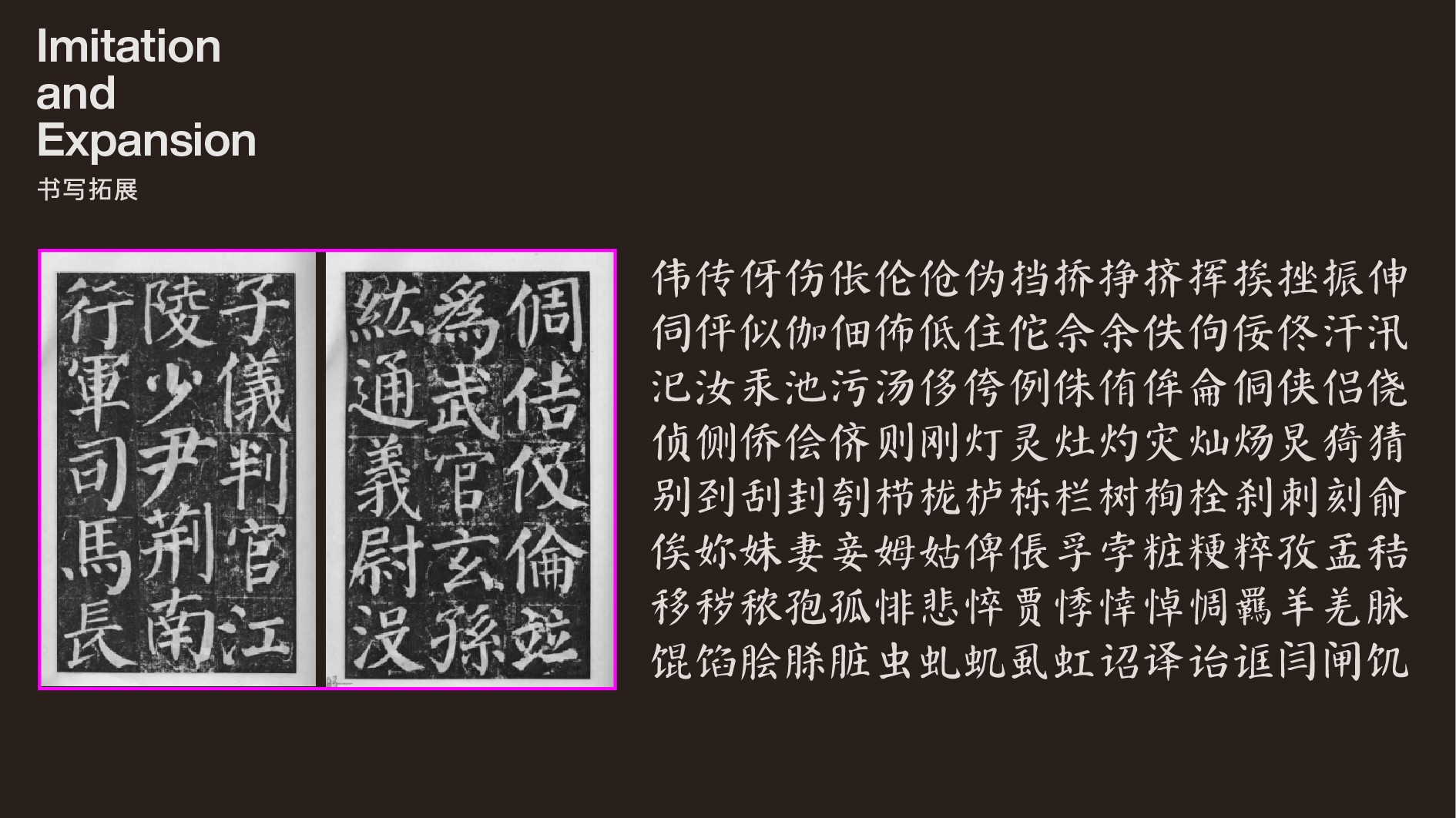
演讲二:非中文字体在中国的需求日益增长
演讲人:方正字库字体设计师 何诗旸
在“一带一路”与全球化交融的浪潮中,何诗旸以《Emerging Market: The Need for Non-Chinese Typefaces in China》为题,揭示了字体设计的另一重使命——成为跨文化的信使。
据调查,中国用户偏好“安全区内的创新”——既追求与国际品牌接轨的相似性,又需保留本土审美特质。因而,方正字库通过“多文种适配”与“区域化调校”,为vivo等企业提供跨语言字体解决方案,实现商业与文化的双赢。
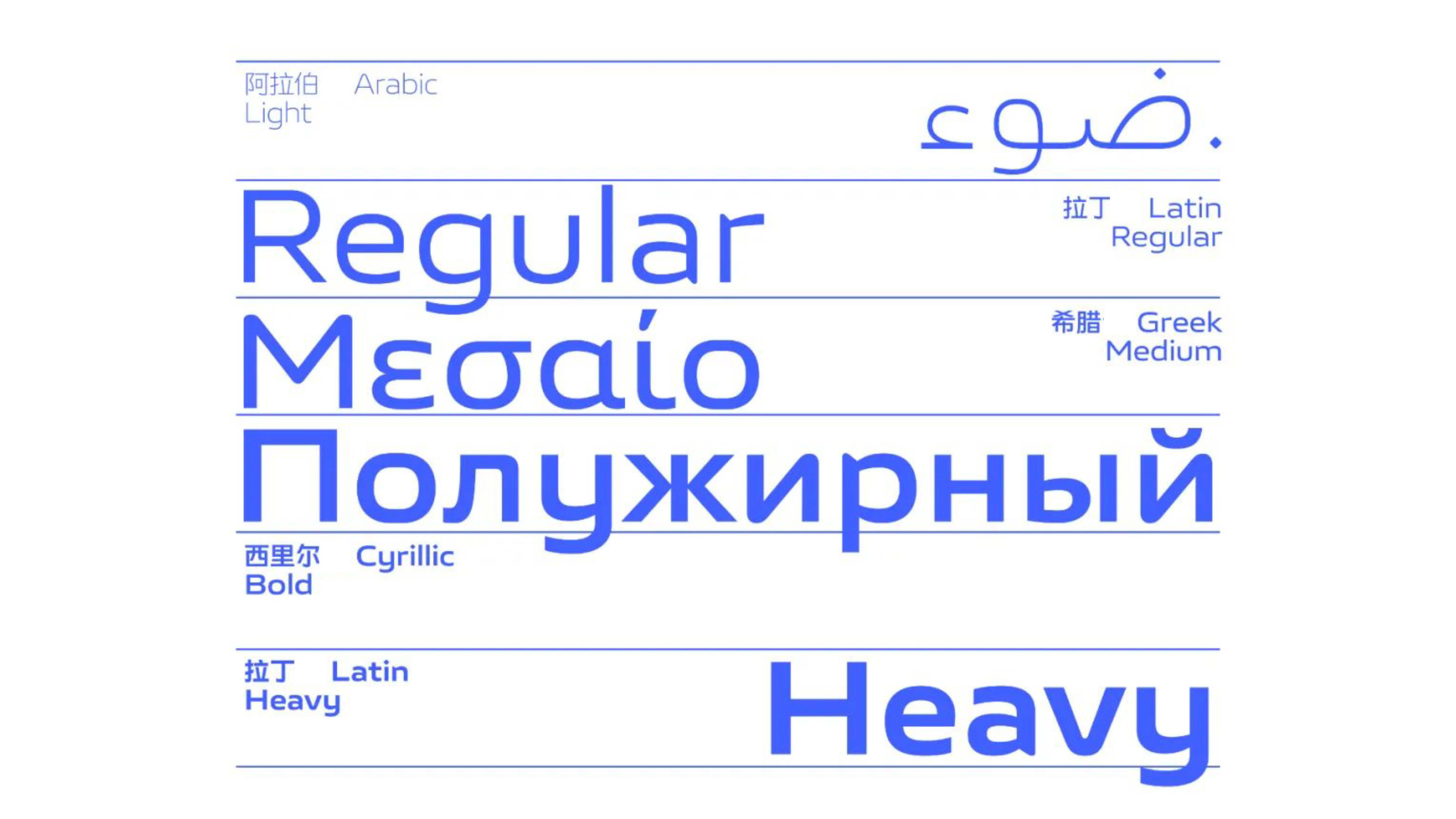
演讲中何诗旸指出,非中文字体不仅是技术产品,更是中国连接世界的文化桥梁。字体设计也不只是字形的构建,更是语言认同、文化传播的重要载体,方正字库正从“汉字守护者”转向“全球字体的整合者”,助力中文与多语言字体的协同创新。
ATypI每一年都汇聚世界各地的专家、设计师,共同探讨新趋势,今年方正字库与众多与会者一同站在 AI 技术与多语系统交汇的关键节点,进行关于AI与排版的探讨,方正字库以持续精进的技术回应着时代的命题,推动“中文字体走向世界”与“全球语言进入中国”的双向通道。